오늘은 창업 이야기 Series_02편~ 무료 폰트를 활용한 로고 만드는 방법을 직접 실습으로 보여드리겠습니다.
실습순서
- 눈누 사이트에 접속하여, 로고 컨셉에 맞는 폰트를 5개 정도 다운로드합니다.
- 포토샵을 실행하여 디자인을 만들어 주겠습니다.
1. 눈누 사이트에서 폰트를 다운로드합니다.
눈누 웹사이트에 접속하여, 상단에 모든 폰트 메뉴를 클릭한 후, 오른쪽에 보시면 허용 범위와 폰트 형태가 있습니다.
허용범위는 BI/CI에 체크를 하고, 폰트형태는 원하는 유형(예시, 고딕체)을 체크합니다.
BI/CI에 대한 이해
우리가 만든 로고는 BI/CI에 속합니다. BI/CI 대해 잠깐 설명 해드리면 CI는 회사의 로고인 코퍼레이트 아이덴티티(Corporate Identity)의 약자고, BI는 그 회사에서 만든 브랜드의 로그인 브랜드 아이덴티티(Brand Identity)의 약자입니다.
LOGO > CI > BI 개념으로 쉽게 이해하시면 됩니다.
- CI는 기업의 정체성
- BI는 기업의 산하에 있는 브랜드의 정체성
폰트 다운로드 하기
허용범위(BI/CI)를 체크하면 무료로 사용가능한 다양한 폰트가 보입니다.
원하는 브랜드 이름을 '예시문구에 입력(예, 즐거운 김씨네)'에 적어주면, 해당 폰트 예시를 한눈에 확인하실 수 있습니다.
저는 1인가족 타켓 밀키트 식품 컨셉에, 브랜드 이름도 '즐거운김씨네' 여서 즐겁고, 활기차고, 건강하고, 상쾌한 느낌의 폰트를 6개 샘플로 선택해 보겠습니다.
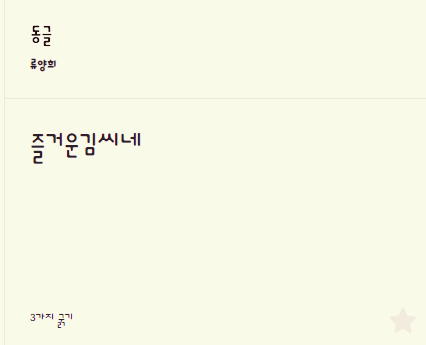
3. 포토샵을 실행하여 디자인을 만들어 비교해 봅니다.
포토샵을 실행하여 디자인을 만들어 주겠습니다. 다운로드하여 설치한 글꼴을 적용하여 비교해 봅니다.
6가지 서체 중 브랜드와 가장 적합한 서체를 고릅니다
저는 1인가족 타켓 밀키트 식품 컨셉에, 브랜드 이름도 '즐거운김씨네' 여서 즐겁고,활기차고, 건강하고, 젊은 느낌의 '동글' 폰트를 선택하였습니다.
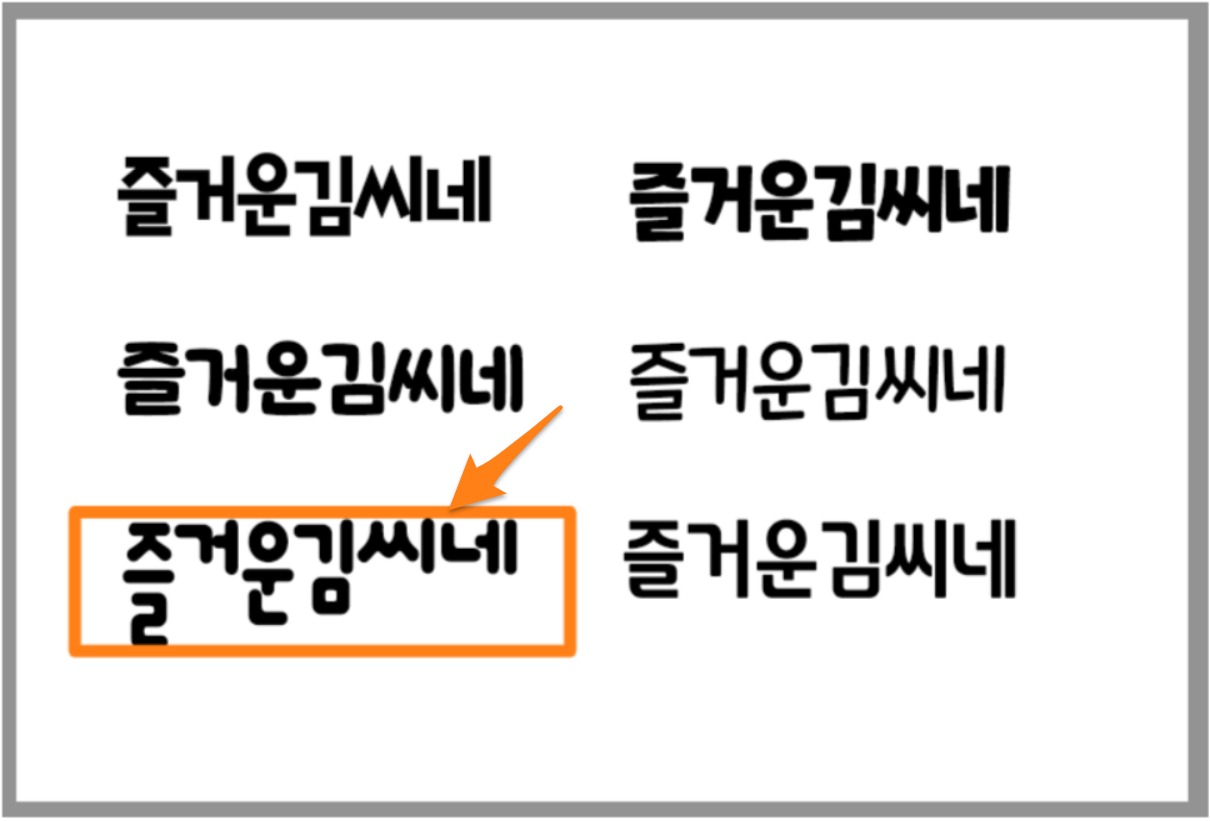
로고 폰트와 잘 어울리는 컬러를 선택합니다
이제 동글 폰트에 색상컬러를 적용해 보겠습니다. 색상선택 시 참고하실 사이트 2개 추천드립니다. 추천 사이트에서 키워드 검색 후 원하는 컬러를 복사하여, 복사한 컬러 코드는 포토샵 문자 패널 색상에서 붙여넣기 합니다
※ adobe color 사이트 예시
사이트에서 키워드 검색 후 원하는 컬러를 복사하여, 복사한 컬러 코드는 포토샵 문자 패널 색상에서 붙여넣기 하거나, 색상을 스포이드로 선택하여 적용해 봅니다.
컬러를 적용해 본 후, 최종 폰트컬러를 선택합니다.
오늘은 무료폰트로 멋진 성공창업 폰트 로고 찾아가는 간단한 실습을 진행해 보았습니다.